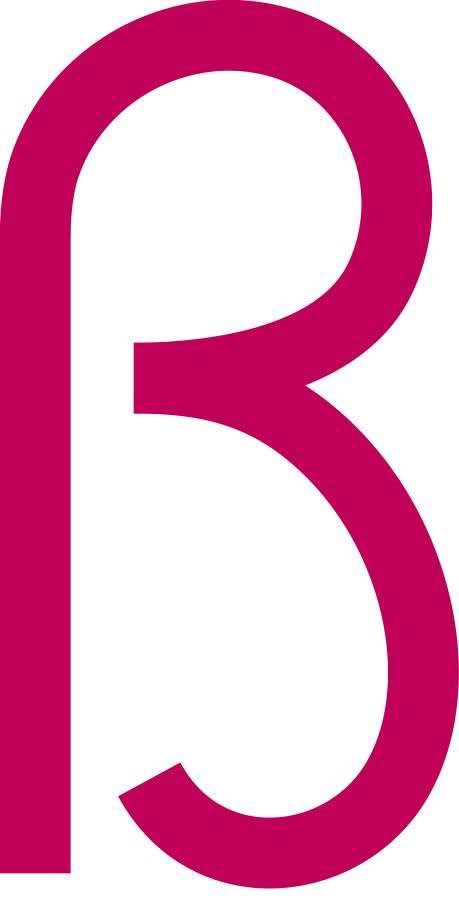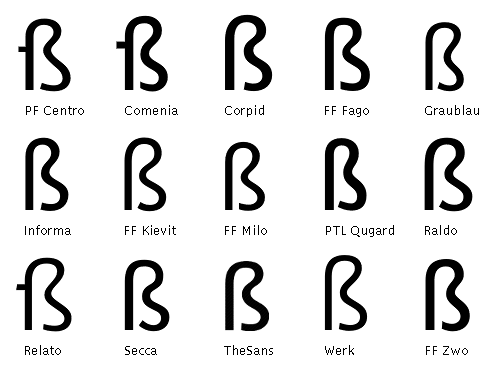
Frutiger-Alternative mit „richtigem“ ß
Ich suche ’ne Alternative zur Frutiger (die mir zu ausgelutscht ist), also eine (mäßig) dynamische, leserliche Grotesk, die allerdings (wie die Frutiger auch) ein Eszett haben soll, das auch aus ? und z besteht:
Die ich kenne haben alle ein ?s: :?
… außer der Colophon und der Arventa, die mir aber nicht so gut gefallen.
Ach ja: Eine „echte“ Kursive sollte sie auch haben.
bleiben wir gleich beim herrn adrian:
okay, nicht abgelutscht war auch noch ein ktiterium :?
aber wenigsten nicht ganz so abgelutscht wie die frutiger.
ich hab beim duchgehen meines fontexplorers den eindruck, die meisten neuen fonts haben ein „ß“, das aus lang-s und rund-s zusammengesetzt ist. die älteren/klassischen eher nicht. dürfte wohl auf die zur jeweiligen entstehungszeit gerade vorherrschende theorie zur genese des ß zurückzuführen sein. :huhu:
warum bevorzugst du die ältere version?
Wie wärs mit der Flama?
... nagut, vielleicht nicht dynamisch genug, genausowenig wie diese hier
NeoSans
Neo Tech
Nudista
Veto
Vialog
... aber wenn man so kapriziöse Wünsche hat, muss man kompromissbereit sein – wobei ich lieber erst gar keine Diskussion darüber anfange, welche ß-Form die Wahre, Schöne und Gute ist.
Immerhin kann man anhand dieser Funde Carlitos Hypothese dergestalt erweitern, dass nicht nur die klassischen Groteskschriften, sondern auch die zeitgenössischen statischen eine Tendenz zur Sulzbacher Form beim ß haben.
na frohe ostern erst mal und mit einen nachtrag zum 1.4., wenn ich sz dann uploeden kann, ein eszet.... :hammer:
Carlito: Die Avenir ist mir nicht dynamisch genug, außerdem hat sie keine richtige Kursive – und ja, sie ist auch etwas zu ausgelutscht …
Scobal: Die Veto find ich zu außergewöhnlich, die Vialog ist mir etwas zu schmal, außerdem ist sie der Frutiger ja zum Verwechseln ähnlich! Deine anderen Vorschläge find ich zu statisch.
TypoLion: Dein Beitrag gibt mir Rätsel auf. Darf ich Dein Eszett in meine Schrift einbauen? :D
Carlito hat sicher recht, womöglich ist Tschicholds ?s-Theorie ja immer noch so weit verbreitet, dabei haben Bollwage und Brekle in den Gutenbergjahrbüchern 1999 bzw. 2001 belegt, daß das Eszett auf eine ?z-Ligatur sowie auf mittelalterliche Abkürzungszeichen aus langem ? mit drangesetzten Haken zurückgeht (und in der Antiqua davon unabhängig eine ?s-Ligatur entstand).
Darum halte ich auch die Sulzbacher Form (?+3) für die „wahre“ und „gute“. Die schönere ist sie meiner Meinung nach auch, das ?s sieht mir immer so danach aus, als hätte der Buchstabe einen Hieb in den Bauch bekommen … :twisted:
Komisch ist jedenfalls, daß auch die neueren statischen Schriften eher zur Sulzbacher Form neigen. :?
na das ist aber jetzt echt "Mafzstab" ...
Komisch ist jedenfalls, daß auch die neueren statischen Schriften eher zur Sulzbacher Form neigen. :?
Vermutlich weil es die geläufigere und gelernte Form ist?
na das ist aber jetzt echt "Mafzstab" ...
In den 1920ern war es mal Mode in Grosteken die scharfen ß wie in den gebrochenen Schriften zu bauen. Ein schönes Beispiel wäre die Erbar, die es digital aber nur noch in einer modernisierten Version als Erbar Condensed von LT gibt. Allerdings waren das durchweg sehr statische und eher geometrische Schriften. Also definitiv keine echte Alternative zur Frutiger.
bei der erbar geht der strich des z-teils aber nicht wie im gezeigten beispiel links aus dem lang-s-teil raus ... ebenso bei den berliner straßenschildern ( >>> cst-berlin west, die hier schon mal thema war. das ist ja alles o.k.
aber der "Mafz?tab" ... nee, nee.
Sorry Joshua! wollte dich nicht auf den arm nehmen, nur ein bischen 1.4.-mäßig, und hinterhältigerweise habe ich dir eine ß geschickt aus einer schrift, die ich noch nicht fertig habe...(siehe unten)
im ernst, ich würde die Formata oder den ITC BQ Franklin Gothic als alternative zum Frutiger vorschlagen, allerdings die Kategorie aus/ab-gelutscht für die Frutiger kann ich nicht nachvollziehen. die abgelutscheste schrift aller zeiten ist doch wohl unsere "gute-alte" autobahn-dinschrift, oder?
in diesem sinne......
im ernst, ich würde die Formata oder den ITC BQ Franklin Gothic als alternative zum Frutiger vorschlagen, allerdings die Kategorie aus/ab-gelutscht für die Frutiger kann ich nicht nachvollziehen. die abgelutscheste schrift aller zeiten ist doch wohl unsere "gute-alte" autobahn-dinschrift, oder?
in diesem sinne......
Bzgl. der Formata stimme ich mit Dir überein. Die Franklin Gothic stößt bei mir aber weniger auf Zustimmung, es ist sogar das Gegenteil der Fall. Vmtl .ist sie auch zu bieder? Hier in Karlsruhe ist die Frutiger aber echt abgelutscht. Verkehrsbetriebe und viele kommunale Einrichtungen nutzen die Frutiger. Aber auch die Avenier ist hier fast schon auf den Weg eine (lokale) Modeschrift zu werden (seit etwa 2007?). Da wäre die Formata sicherlich weniger vorbelastet.
RobertMichael, Danke für die Vorschläge! Die Alright gefällt mir ziemlich gut: Wie die Franklin und die News Gothic, aber mit offeneren Formen und besserer Kursive.
Die anderen sind mir in dem Fall zu statisch, aber die Encore muß ich mir mal im Hinterkopf bewahren, die gefällt mir auch gut.
Gerade hab ich auch durch Zufall auf meiner Bitstream-CD die Chianti entdeckt, die auch nicht schlecht ist. :D